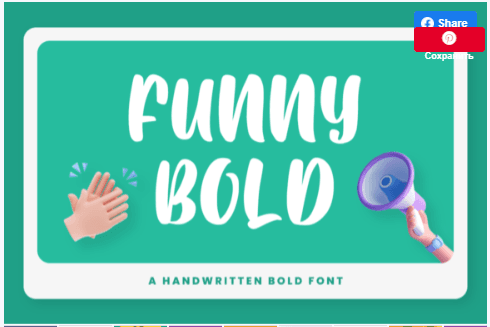
Funny Bold Font
Funny Bold - это забавный, непринужденный и дружелюбный дисплейный шрифт. Используете ли вы его для творчества, цифрового дизайна, презентаций или изготовления поздравительных открыток, он идеален!